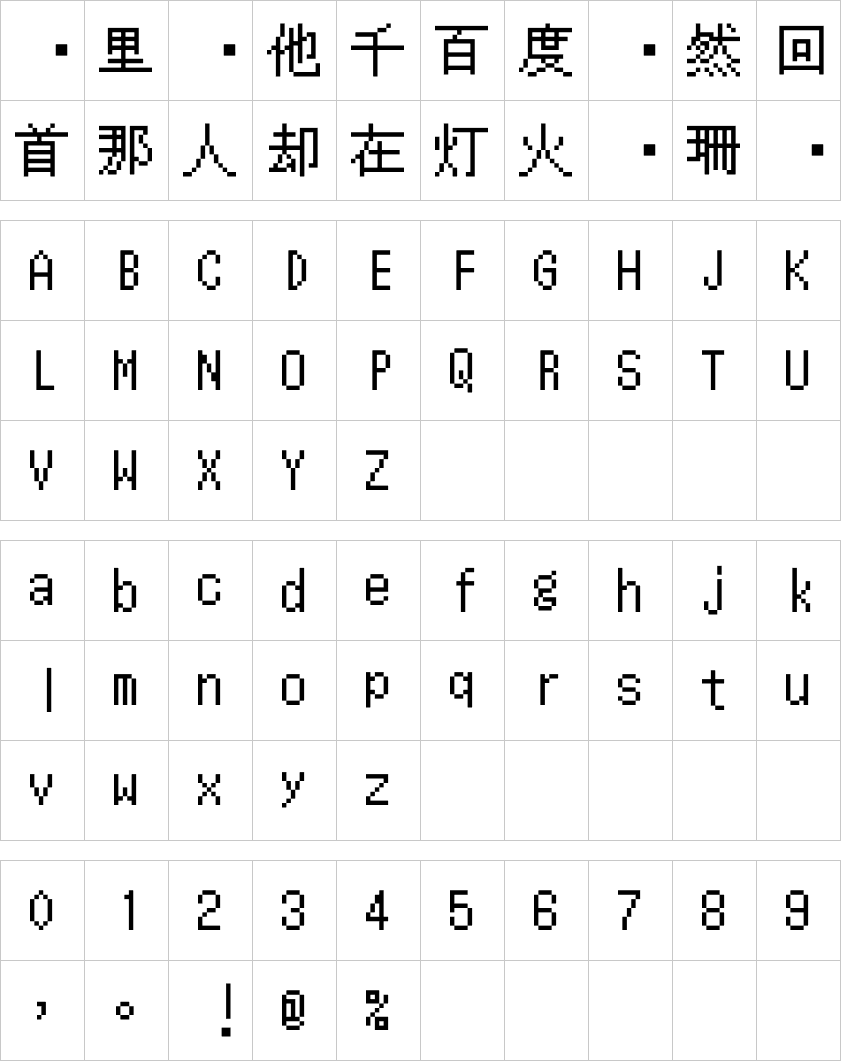
KHドット小伝馬町
KH点字体是由粗糙点构成的位图风格的字体系列,由表情丰富的15个字体构成。这些都是TrueType格式的等宽轮廓字体,可以在Windows、Mac、Linux等各种环境中使用。
本字体系列是由字体设计师平木敬太郎从1991年到1996年设计的,现在作为面向X68000系列(1987年发售的夏普电脑系列)等形式发布的高品质的点字体自制字体工作室重新配置为TrueType格式。